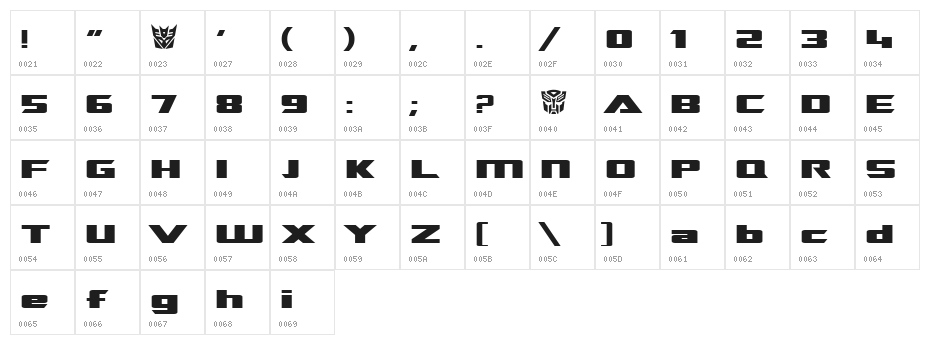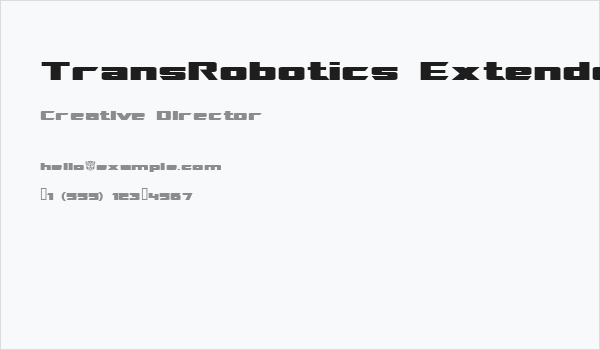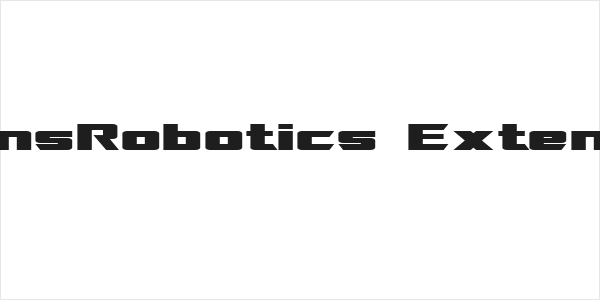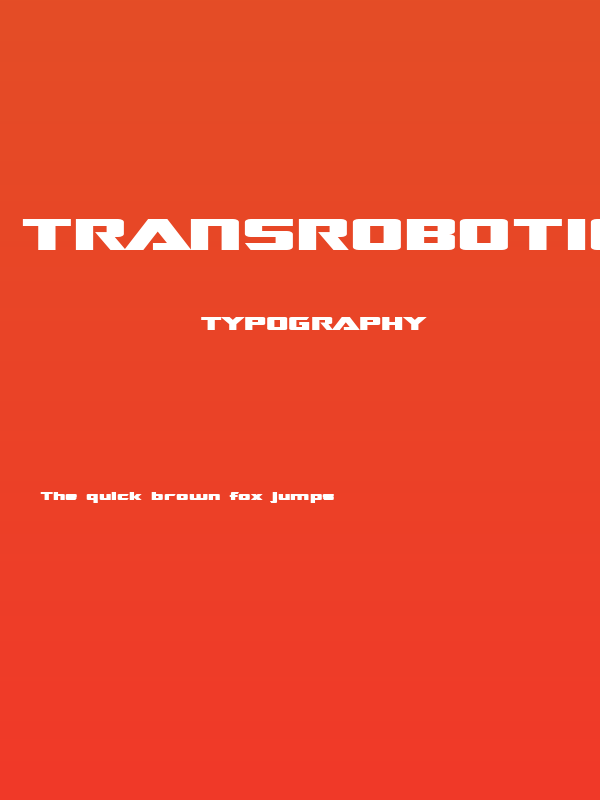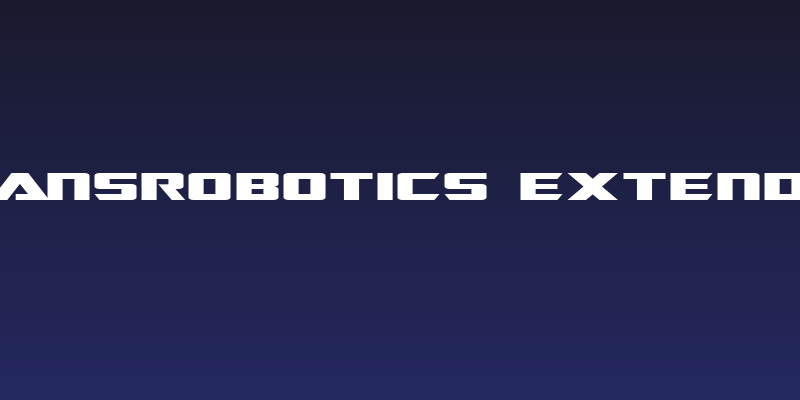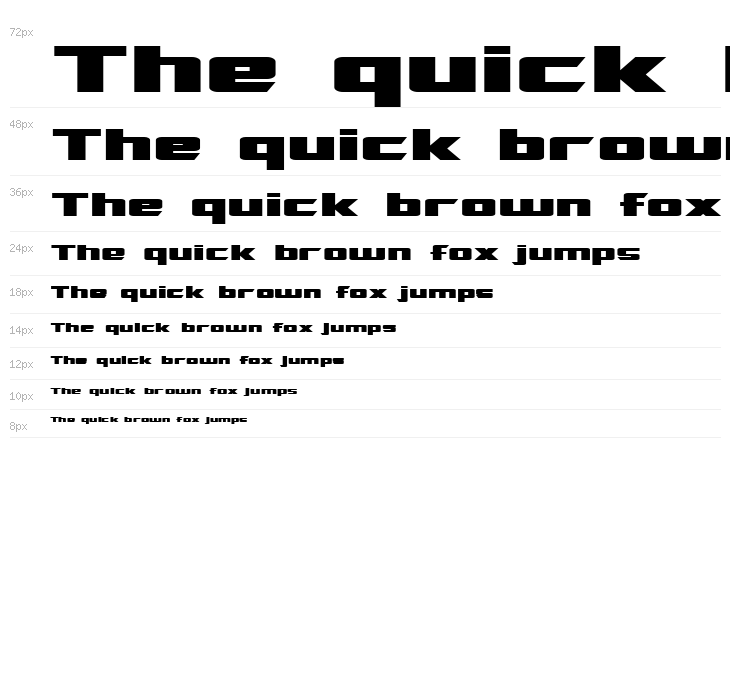
TransRobotics Extended Font
✎ Decorative
| Proyectos propuestos | Ideal for sci-fi themed designs, tech branding, video game titles, and futuristic posters. |